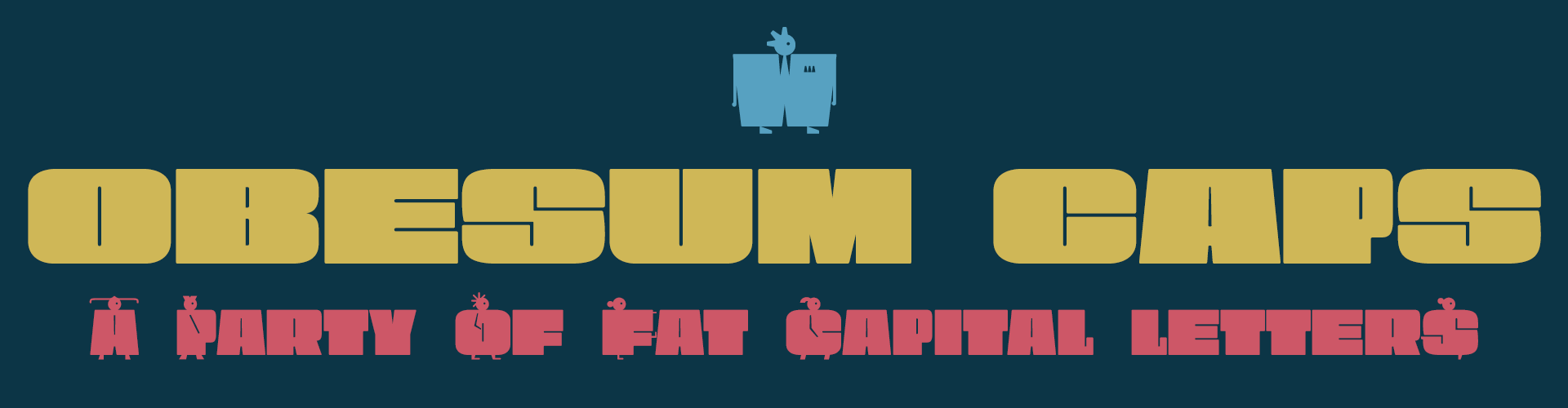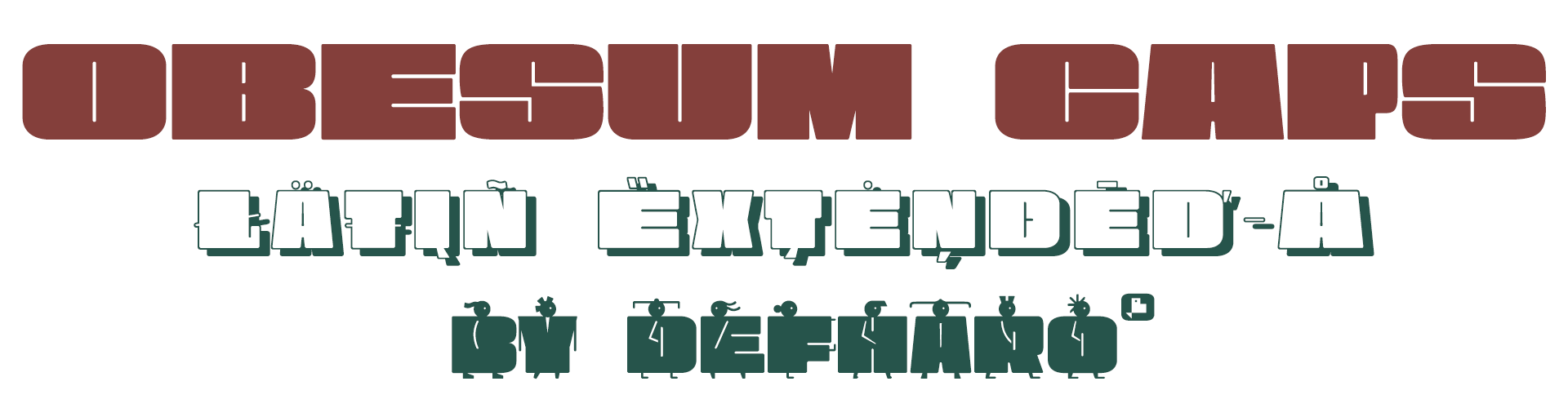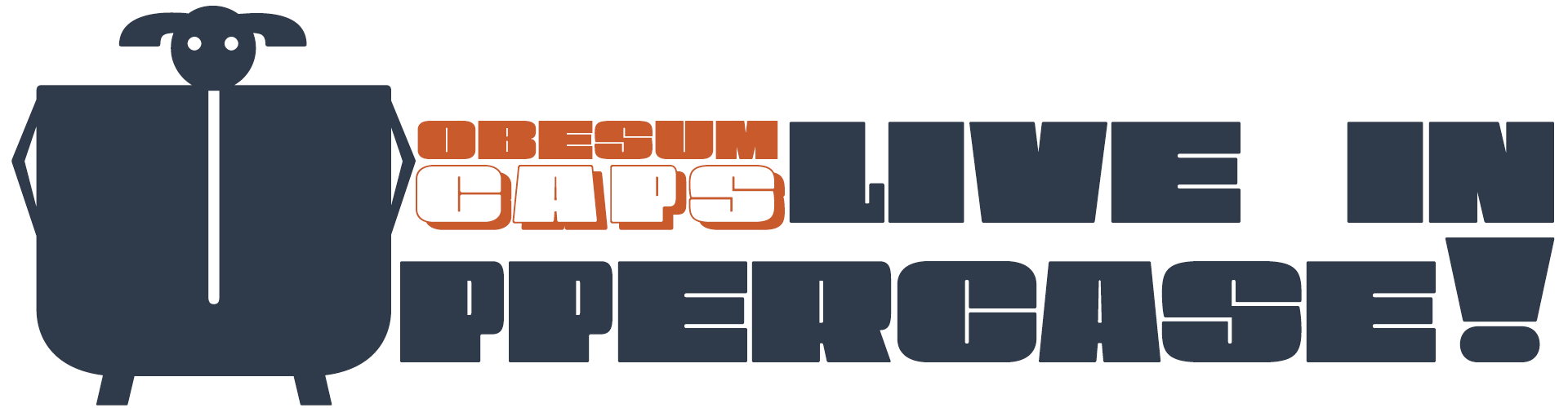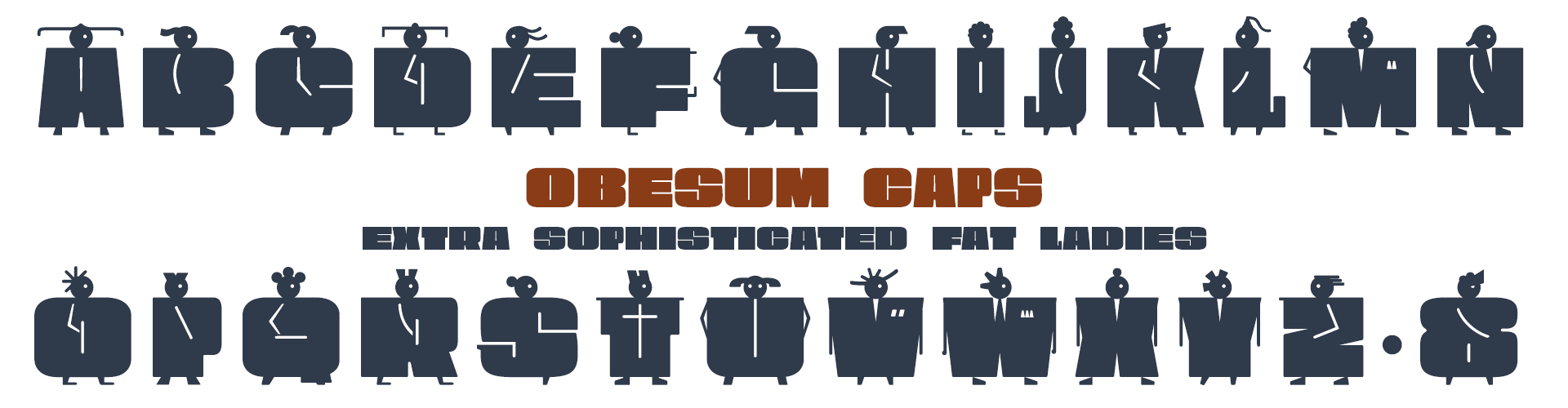
Display Font
Estilo: Sans, Display, Fat, Geometric, Shadow
Proporción: Extended, Square
Funciones OpenType: All Alternates, Alternate Annotation Forms, Bitcoin, Capital Spacing, Contextual Alternates, Denominators, Discretionary Ligatures, Extended Fractions, Historical Forms, Historical Ligatures, Kerning, Localized Forms, Numerators, Oldstyle Figures, Ordinals, Scientific Inferiors, Slashed Zero, Standard Ligatures, Stylistic Set, Subscript, Superior letters, Superscript.
He disfrutado tanto con las formas y contraformas de esta tipografía que he dibujado un alfabeto completo alternativo a las letras minúsculas con figuras de chicas obesas muy sofisticadas que se van de fiesta, espero que te guste.